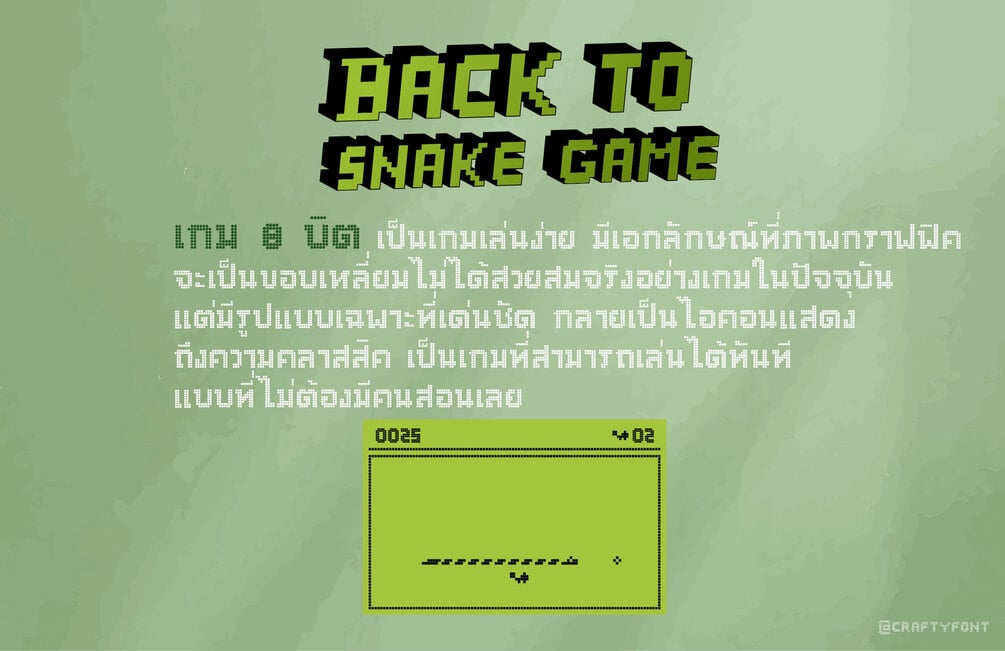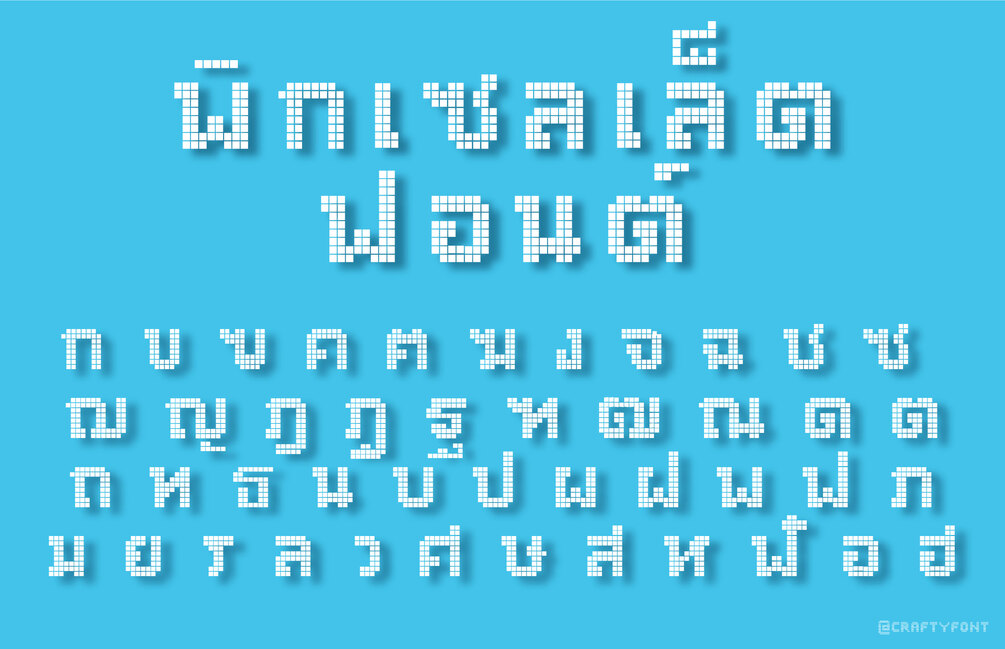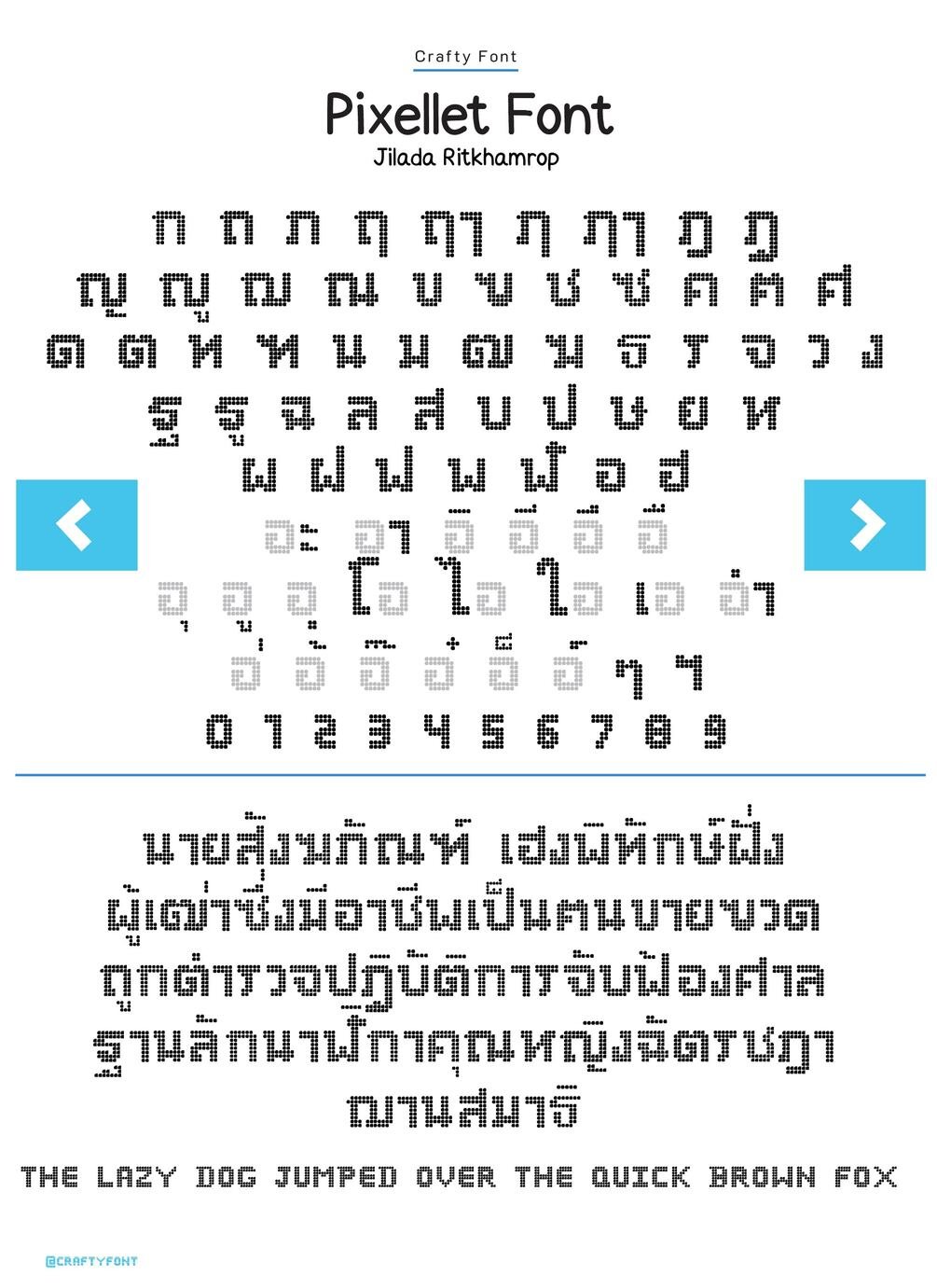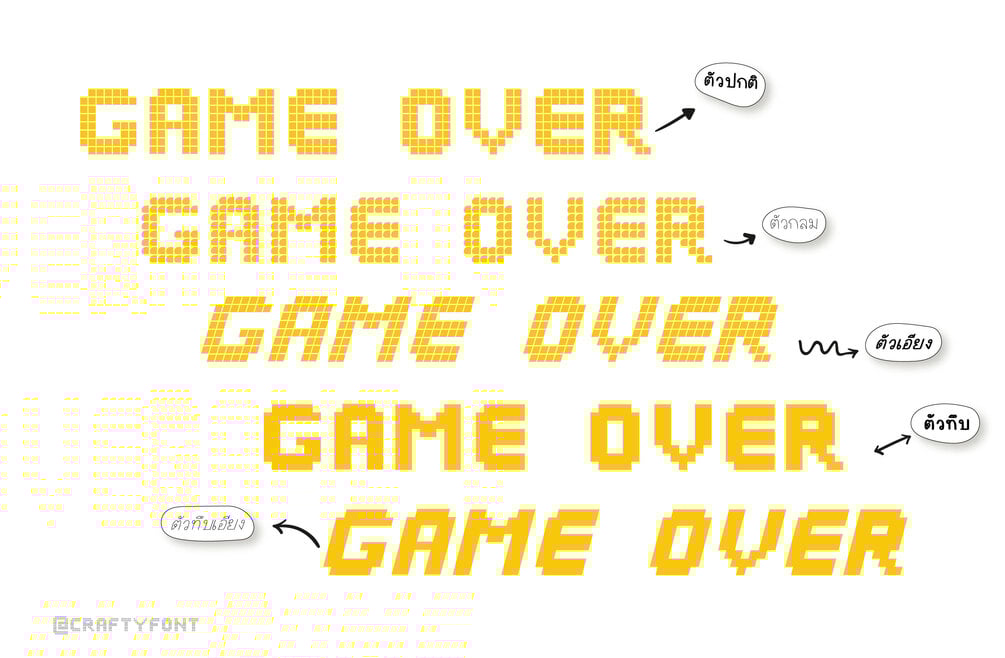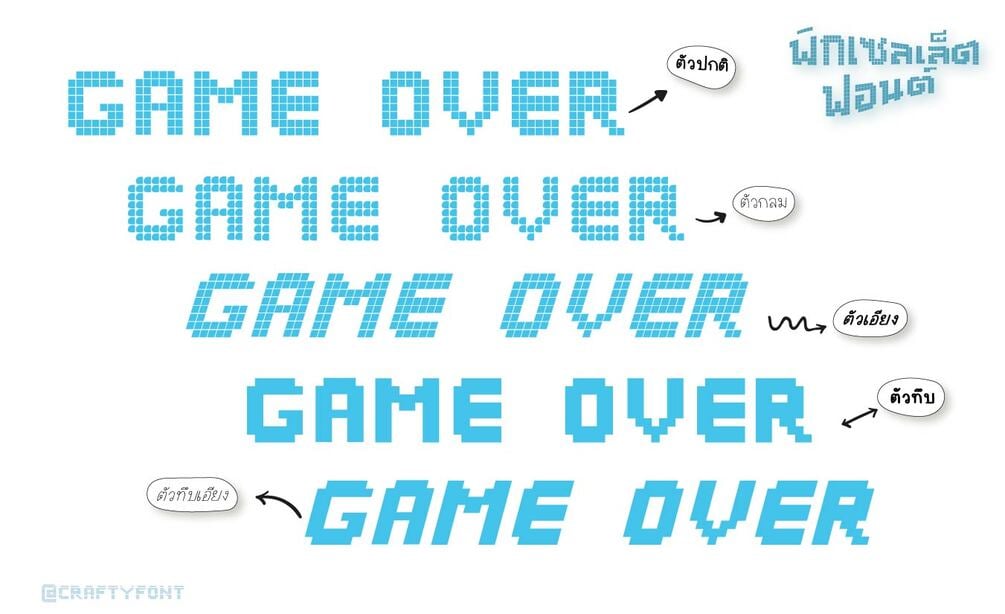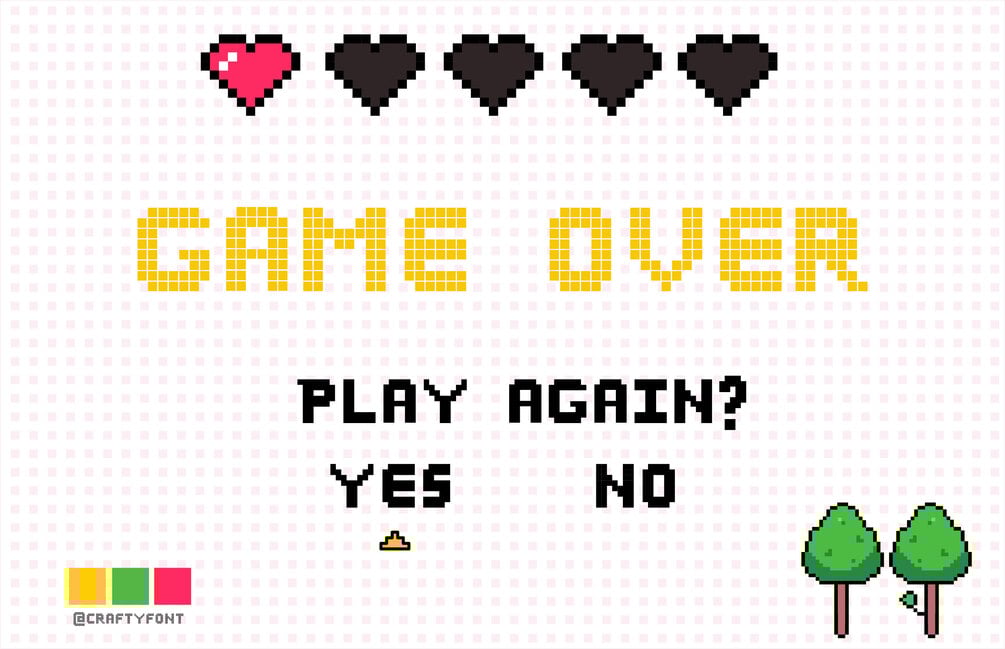
Pixellet Font (ฟอนต์พิกเซลเล็ต)
ฟอนต์พิกเซลเล็ต มาในรูปแบบตัวเม็ดพิกเซลสุดคลาสสิก ตอนแรกกะจะทำแบบแถวเดียวทึบ ให้ความกว้างไม่เกิน 5-6 เม็ดพิกเซล แต่ทำไปทำมาบางตัวกว้างไปถึง 12 พิกเซลเลย แหะๆ 😅
แต่รวมๆ แล้ว น้องก็ดูน่ารัก อวบอ้วน สไตล์ Crafty font ดี เลยทำต่อไปจนครบทุกตัวอักษร
พิกเซลเล็ตมีตัวปกติ ตัวทึบ ตัวเอียง ตัวทึบเอน และแบบกลม
***ฟอนต์ Pixellet ภาษาอังกฤษไม่มีตัวพิมพ์เล็ก และภาษาไทยไม่มีเลขไทยนะคะ แต่สามารถพิมพ์ได้ปกติค่ะ
****ไม่มีตัว & พิมพ์แล้วจะไม่แสดงผล ไม่ได้ทำใส่ไปฮะ